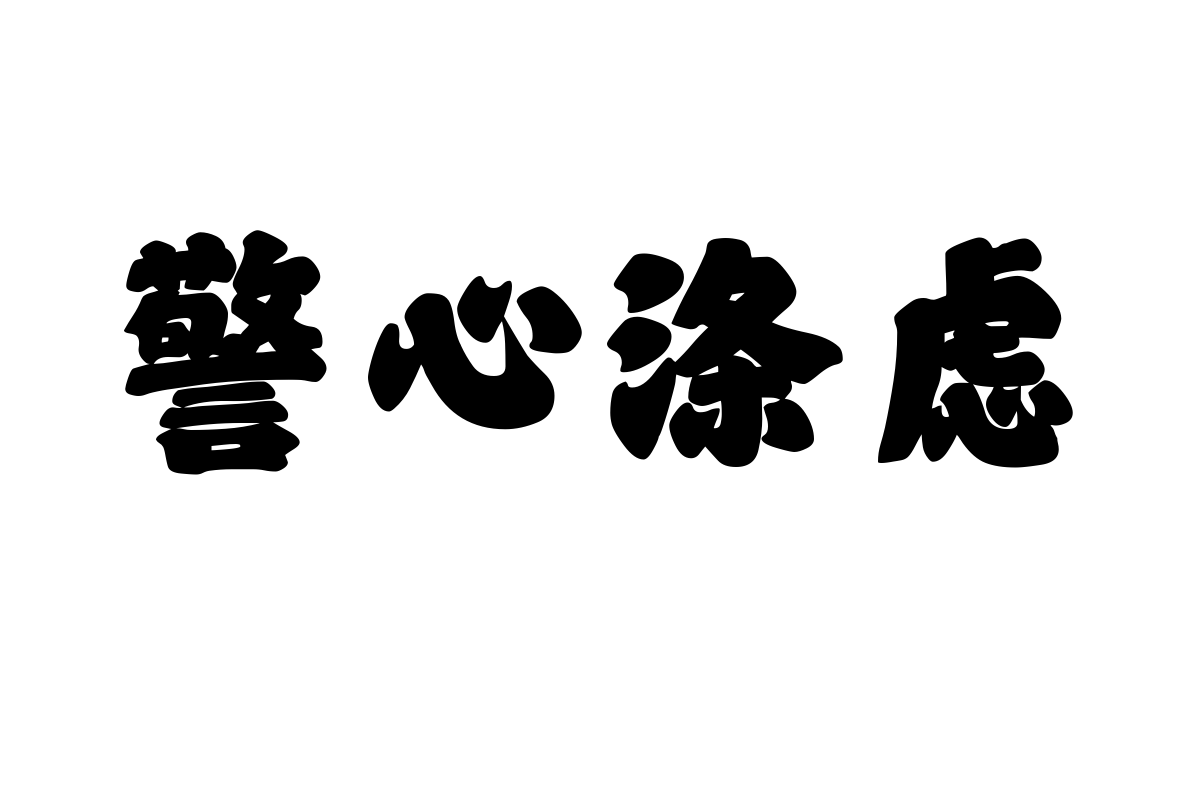
**山海战魂榜书W是一款中文字体,包含9169个简繁汉字**。
山海战魂榜书W的字体大小为5.89Mb,格式为ttf,适合在Windows系统上使用。这种字体的设计灵感来源于古代战场上的战魂,通过粗犷有力的字形和雄健的力量感,展现出一种强烈的视觉冲击力和历史沉淀感。其特点在于非常规的张力特性,使得书写时能够更好地表达出文字所蕴含的情感和力量。